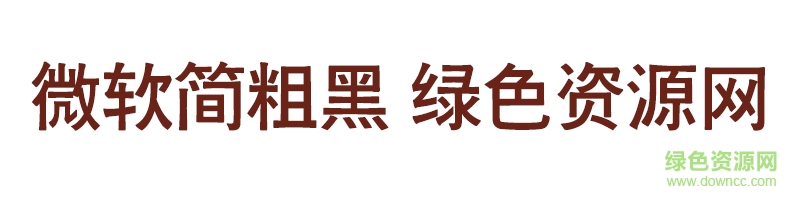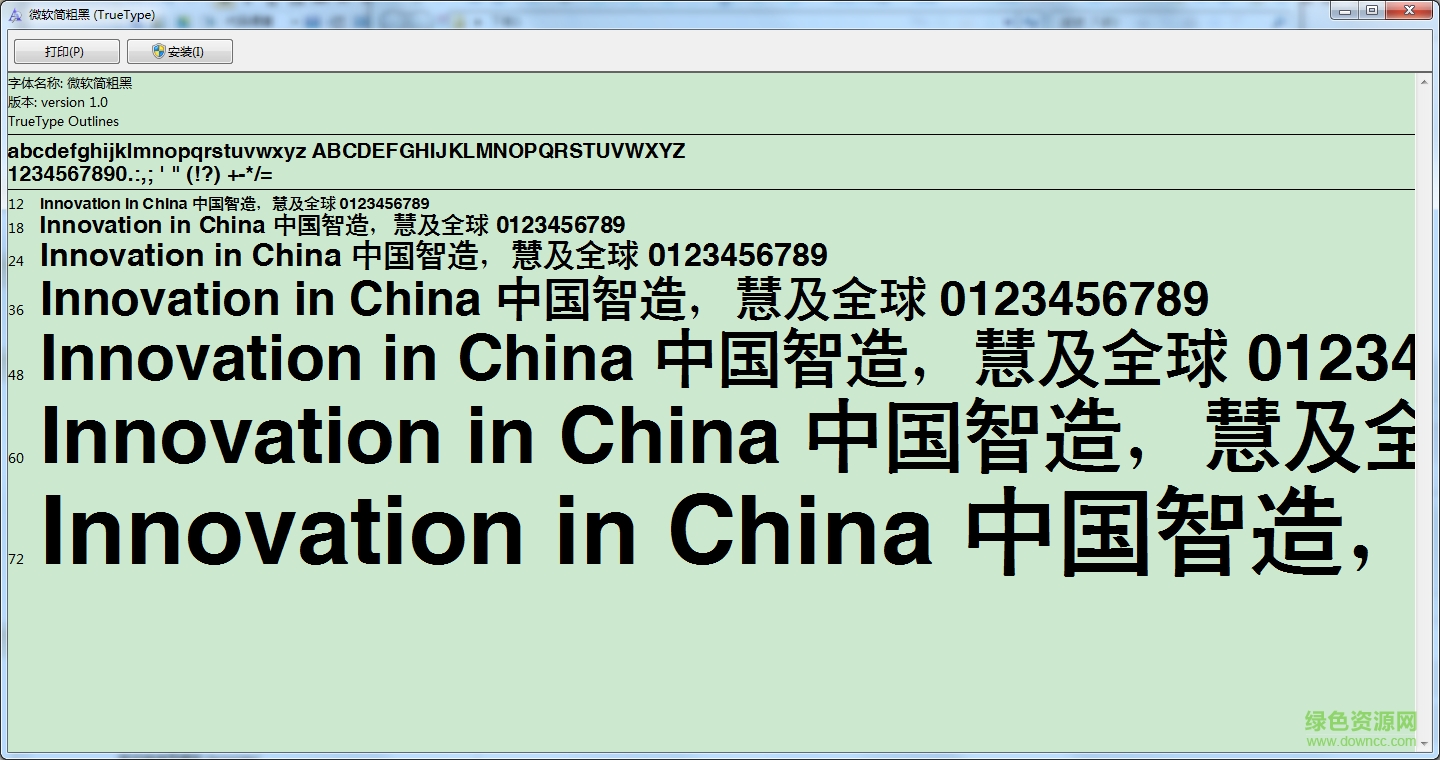
微软简粗黑
微软简粗黑字体是一款比较常用的windows字体,此款字体以粗黑的方式比较引人注目,非常适用于各种大型宣传活动,全面的适用于各个微软系统,欢迎来绿色资源网下载!
微软简粗黑特点
微软简粗黑字体结构严谨、字形端正、笔画横平竖直,字形风格中正刚肃,笔画首尾巧用圆角,令其在古朴沉厚的同时又不失和柔儒雅之风。